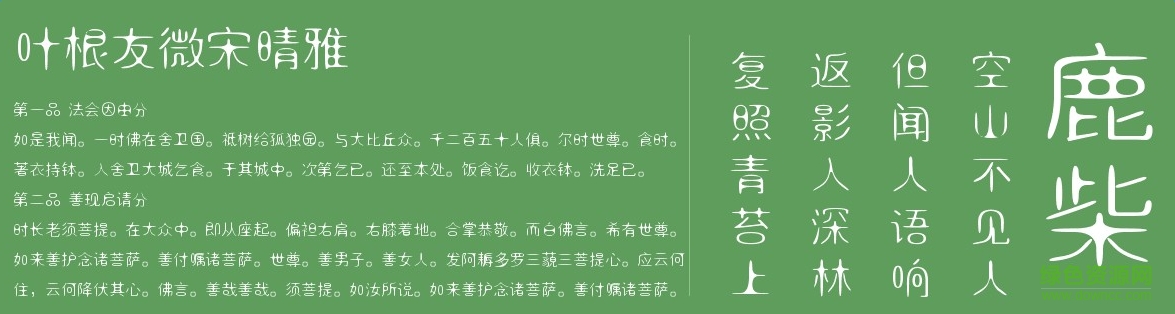
葉根友微宋晴雅
葉根友微宋晴雅字體是一款由知名書(shū)法家葉根友創(chuàng)造的字體,比劃圓潤(rùn),適用于廣告、藝術(shù)設(shè)計(jì),海報(bào)設(shè)計(jì)等方面,有需要的朋友們不要錯(cuò)過(guò)了。歡迎大家來(lái)綠色資源網(wǎng)踴躍下載哦!
葉根友微宋晴雅是一款柔性的字體,比較適合內(nèi)文排版和追求時(shí)尚一族的應(yīng)用,圓潤(rùn)的筆畫(huà)線條是這款葉根友微宋晴雅字體的特征,希望大家喜歡。
葉根友微宋晴雅字體,用途廣泛,是葉根友先生的印刷字體,適合場(chǎng)合很多,字體看起來(lái)比較正式。各位字體收藏者可以來(lái)看看。